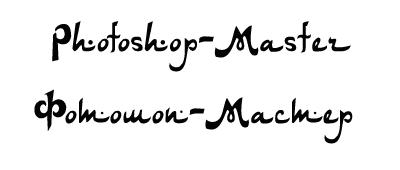
Шрифт - DS Arabic
Интересный шрифт, который хорошо подходит для работы в фотошопе. Есть поддержка русского языка.
Один из лучших, представленных в арабском стиле шрифтов на этом сайте.
нравится очень) сразу такое восточно-индийское настроение создет
Классный шрифт! Очень красивый!!)) оригинальный, в восточном стиле)